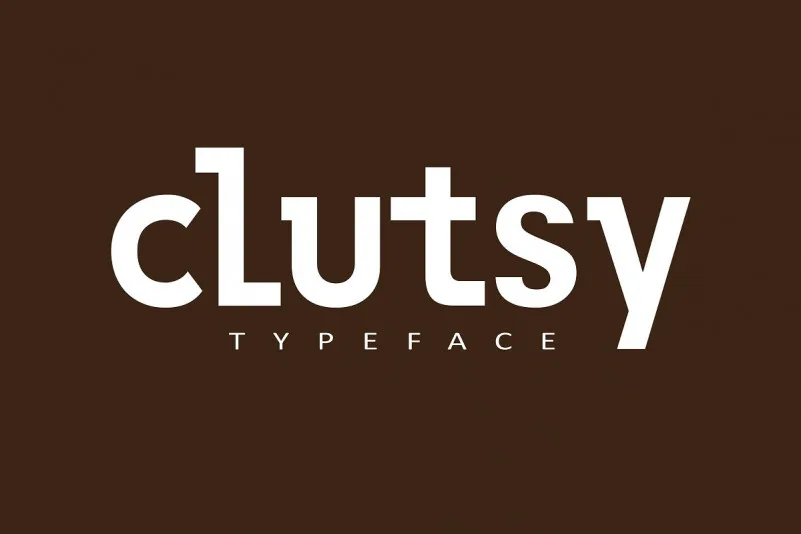
Introduzimos a fonte serifa slab “Clutsy Font”, uma nova criação do designer aminmario. Clutsy é uma família de tipos para fins visuais, com um toque leve e moderno. Embora tenha sido projetada principalmente para uso em letras maiúsculas, incluímos também um conjunto minúsculo caso seja necessário. Clutsy oferece um estilo alegre e robusto, perfeito para aplicações como headlines, logotipos, convites, livros, citações, marcação e qualquer coisa que precise se destacar e fazer uma declaração. Esta fonte é só negrito, com sua natureza extensa garantindo clareza leitura mesmo em dimensões de texto muito pequena. Clutsy é altamente versátil, suportando idiomas múltiplos, tornando-a ideal para projetos que exigem grande destaque e impacto visual. Sem sombra a não ser a negrita, Clutsy se assemelha mais a uma fonte de display, mas mantém seu caráter moderno e elegante. É perfeita para qualquer aplicação que precise transmitir força e estilo.